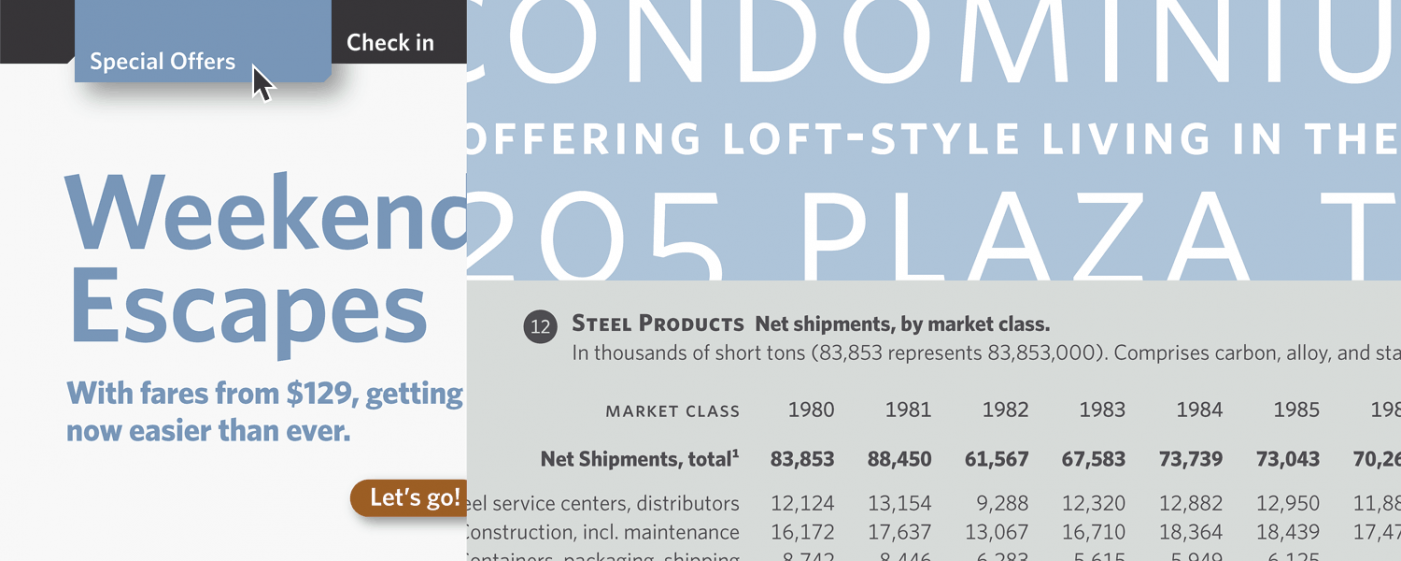
Suche Linotype Syntax mit runden Punkten (oder ähnlich)
weiß jemand von euch, ob es bestenfalls einen Schriftschnitt der (Linotype) Syntax gibt (außer Serif und Letter), bei dem sämtliche Punkte rund statt eckig sind, evtl. unter einem anderen Namen? Da ich nach langer Suche stark daran zweifle, würde ich mich auch über alternative Schriften freuen, die der Syntax möglichst ähnlich sind (serifenlos, humanistisch, rechtwinklige Strichenden, ähnliche Winkel beim W und M), aber eben mit runden Punkten. Ich sehe auch ein, dass vermutlich nicht all meine Wünsche erfüllt werden können.
Eine Syntax-Version mit runden Punkten ist mir nicht bekannt. Aber es gibt viele ähnliche Schriften mit humanistischem Skelett, a mit Schwänzchen etc. Du könnest Dich zum Beispiel mal hier umsehen:
Neben der Alegreya und Today Sans kommt der Syntax vor allem die Eau de Garamond sehr nahe (diese befindet sich aber leider noch nicht im Font-Wiki).
Danke, Robert. Die Eau de Garamond ist schon ganz gut.
Aber keine hat die rechtwinkligen Linienabschlüsse. Auch keine der vielen Schriften, die ich von Anbietern als -  vermutlich automatisch generierte - Alternativen angeboten bekommen habe. Gibt es überhaupt eine zweite Schrift mit diesem Merkmal neben der Syntax, oder ist das ihr Alleinstellungsmerkmal?
Nachtrag: OK, ich sehe, es gibt z.B. die Regulator. Aber die hat sonst kaum Ähnlichkeiten mit der Syntax.
Auf das Schwänzchen beim a könnte ich tatsächlich verzichten, wenn dafür mehr der übrigen Kriterien (serifenlos, humanistisch, rechtwinklige Strichenden, ähnliche Winkel beim W und M)  durchkämen.
Eine Schrift ähnlich der Gill Sans mit rechteckigen Strichenden würde dem Ziel auch nahe kommen. Das M wirkt hier, wie die Schrift im Vergleich zur Syntax insgesamt, etwas starr, was auch schade ist, aber ein Kompromiss.
@Ralf: Ich weiß, es klingt etwas spitzfindig, aber auf genau diese Anwendung bezogen wären runde Punkte, und damit Querschnitte eine Zylinders, schon großartig.
Also das klingt jetzt nicht danach, als ob du Unmengen von Text setzen wolltest … Kann man den Schriftzug dann nicht aus der Syntax nehmen und die Punkt von Hand ändern?
es soll schon auch etwas mehr Fließtext werden. Bei einem Logo würde ich es mir überlegen.
Ok, die von dir ins Spiel gebrachte Zylinderform hat mich eher an ne Werbetechnikanwendung denken lassen.
Nach vielem Liebäugeln kleb ich nun doch wieder an der Syntax, bestenfalls auch noch an der Syntax Next.
Meine bisherigen Ansätze, ausgehend von der Syntax:
FacileSSK nutzen. Die ursprüngliche Herstellerfirma ist erloschen. Nah an der Syntax. Zu nah? Ist die Schrift damit frei nutzbar? Kann da jemand etwas zur Rechtslage sagen?
Dürfte ich die sogar meinen Wünschen (runde Punkte, evtl. offenes R) entsprechend anpassen?
Ich finde es ja (fast) merkwürdiger die Kopien zu kaufen, statt die Kopie des erloschenen "Herstellers" zu nutzen. Freue mich aber auch über Hinweise hierzu. Sieht jemand einfache Lösung, die ich übersehen habe? Oder zumindest eine bessere unter den oben genannten?
Nun, das regelt einfach die Lizenz, und was da im Lizenzvertrag steht, den man ja mit Kauf dieser Lizenz zugestimmt hat. Wenn die eine eigene Bearbeitung, auch nur für eigene Zwecke ausschließt, was so in den meisten kommerziellen Lizenzverträgen so steht, ist das dann eben so.
Und wenn man diese dann als Webfont einsetzt, macht man diese Änderung ja öffentlich, so dass der Schriftenanbieter dies theoretisch auch sehen kann, und damit natürlich das Recht hätte, den Lizenzvertrag, den man ja gebrochen hat, zu kündigen.
Ein Auto tiefer zu legen wäre dagegen ja schon legal, trotz möglicher ästhetischer Bedenken.
Dass die Nutzung oder Bearbeitung jemand rechtlich verfolgt, ist kaum zu erwarten. Die SSK-Fonts waren aber allesamt illegale Klone. Weder Schriftgestalter noch Schriftanbieter haben der Verbreitung als SSK-Fonts zugestimmt oder diese bezahlt bekommen. Zumindest moralisch sollte man um solche Fonts einen großen Bogen machen.
Ich würde die Nutzung der FacileSSK ja auch gerne umgehen. Aber weder finde ich die Syntax Next ohne Tracker und auch die "Struktur Pro" ist zumindest einem Klon sehr ähnlich.